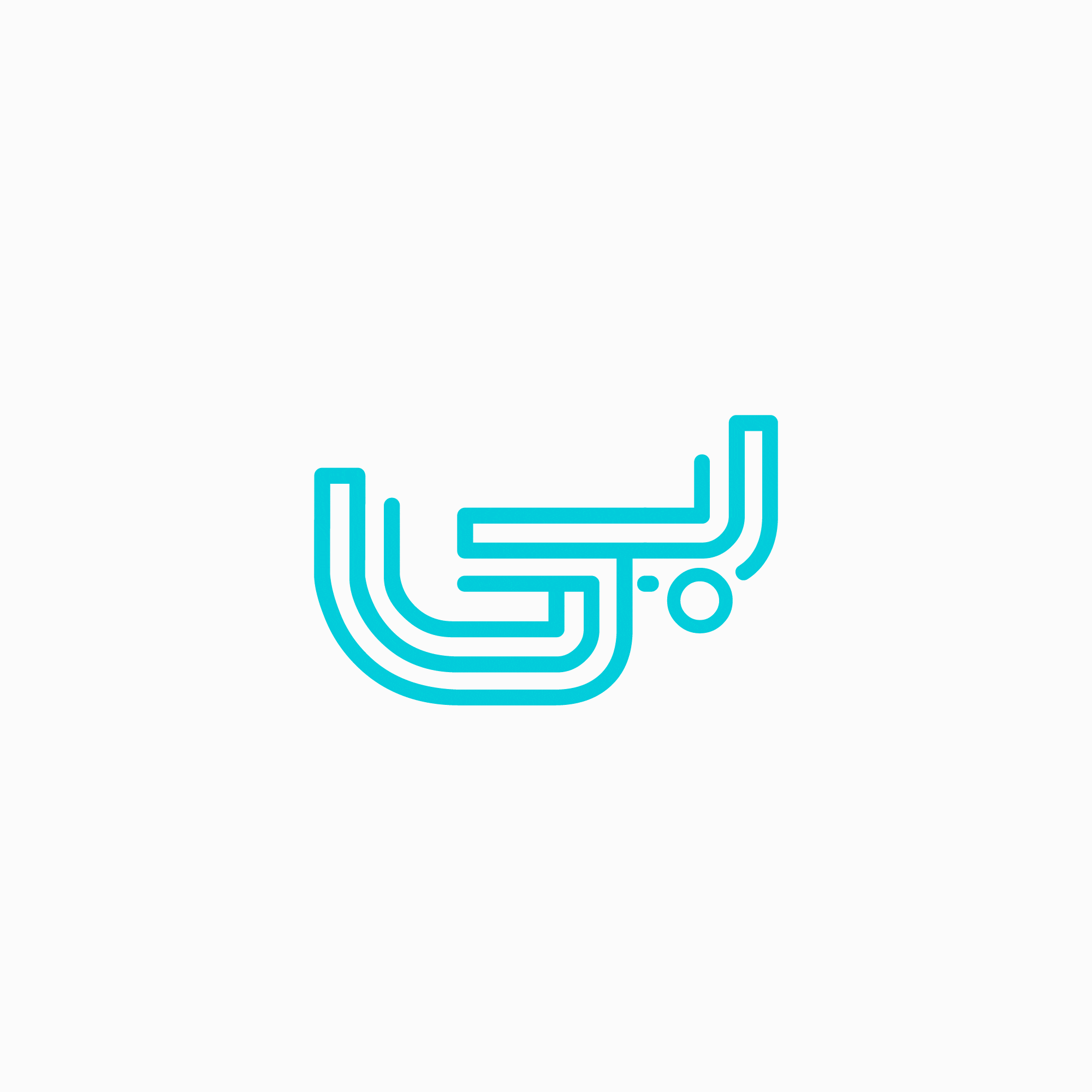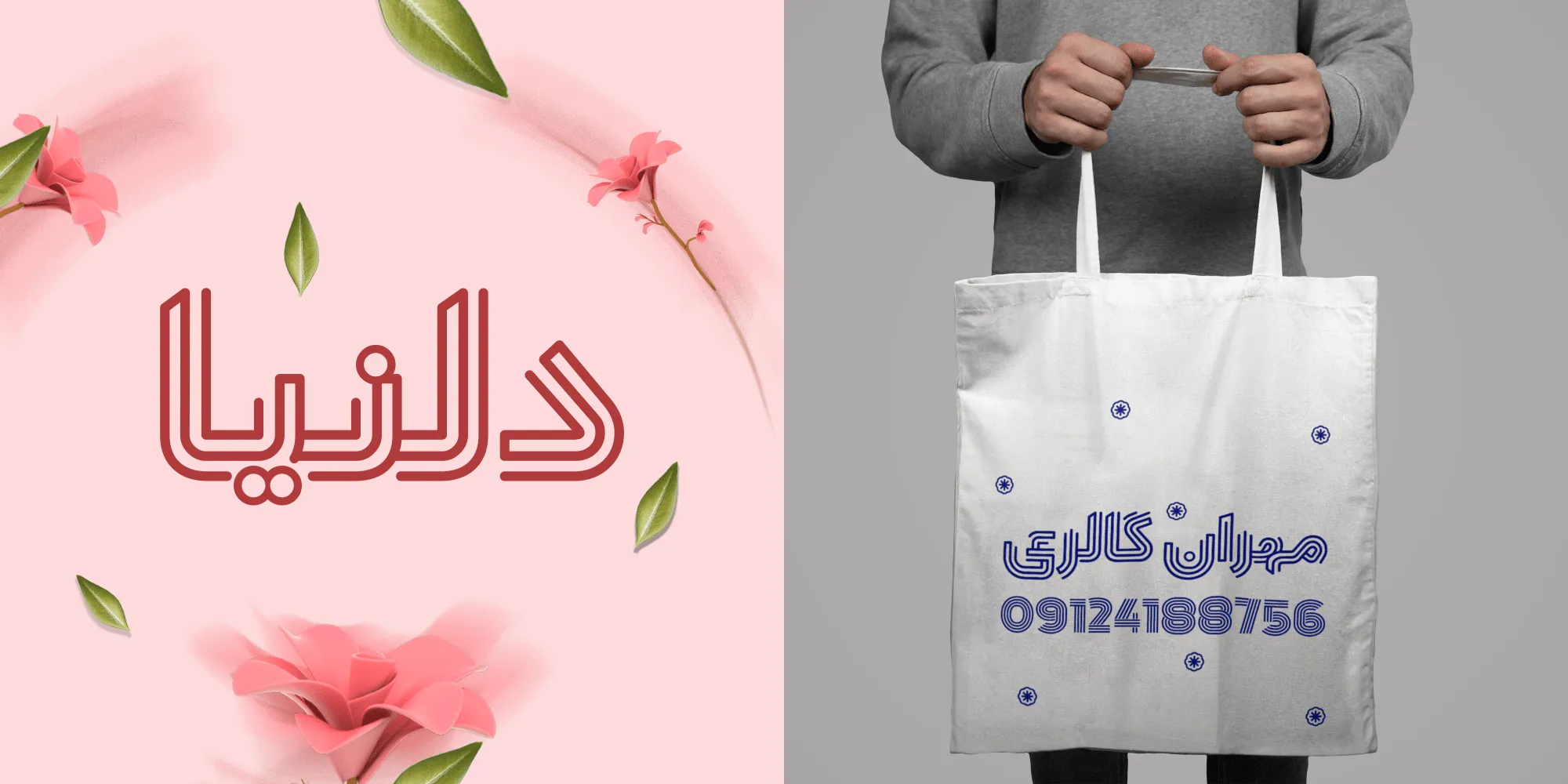
فونت دلنیا (Delnia)
فونت دلنیا (به انگلیسی: Delnia) یکی دیگر از فونتهای جدید فانتزی فارسی است که با سبک مونولاین طراحی شده است که از این قلم میتوانید در کارهای گرافیکی که جنبه تزئینی و نمایشی دارند استفاده کنید. این فونت بر اساس سبک هندسی طراحی شده است. فونت دلنیا رایگان نیست و با توجه به اینکه در یک وزن با قابلیت استفاده از حروف جایگزین، ارائه شده میتوانید آن را در قالب یک بسته نرمافزاری خریداری کنید.
فونت دلنیا توسط مزدک کیانی، طراح تایپفیس و لوگوتایپ طراحی شده است که دارای یک وزن ضخیم Black میباشد که در طراحی تمامی حروف فارسی و غیرفارسی از سبک مونولاین بهره میبرد. توسعه نرمافزاری این قلم نیز توسط امین عابدی که از طراحان و توسعهدهندگان پرکار فونت فارسی است صورت گرفته است.
در ادامه این نوشته از سایت فونتچی به نقد و بررسی کامل فونت دلنیا خواهیم پرداخت؛ قلمی که با توجه به سبک اینلاین میتوانید از آن در انواع کارهای گرافیکی تبلیغاتی که جنبه نمایشی و استفاده برای عناوین دارد بهره ببرید.
فونت Delnia قلمی با ساختار مونولاین است. یعنی با ترکیبی از چند خطوط که به موازات هم قرار گرفته و ظاهری تو خالی از رنگ سفید و مشکی دارند طراحی شده است. این قلم دقیقا ساختاری مشابه فونت ارژن را دارد با این تفاوت که وزن بیشتری را شامل میشود و همچنین خطوط اینلاین، به شکلی درون خطی ادامه دارند.
سبک طراحی و وزن فونت دلنیا
فلسفهای که در پشت فونتهای هندسی، بهویژه آنهایی که با هدف تزئینات و عناوین طراحی شدهاند جلب توجه کاربران است. فونت دلنیا نیز با همین رویکرد با هدف ایجاد مکث و تمرکز خواننده بر محتوا طراحی شده است؛ بهطوری که با صرف زمان بیشتر اطلاعات در ذهن مخاطبان ماندگار شود.
از همینرو با توجه به فضاهای مثبت و منفی در کنار گردش حروف فارسی تصمیم بر آن شد که خطوط بر محیط فرم و گاها در داخل فرم هر نویسه گردش کرده و با ایجاد برشهایی منطقی در فرم نویسهها، این فرصت در اختیار مخاطب قرار داده شود که ذهن او فرم حروف را تکمیل نماید. این امر منجر به افزایش زمان، جهت مطالعهی محتوای مورد نظر را در پی دارد و در نتیجه محتوا نیز در ذهن او ماندگارتر میشود.
پشتیبانی از زبانهای فارسی و لاتین
فونت فارسی جدید دلنیا محدود به این زبان نیست. به لطف اینکه رسمخط فارسی در سایر زبانهای عربی، اردو، کوردی و… که عمدتا شامل زبانهای خاورمیانهای هستند مورد استفاده قرار گرفته است، از این فونت میتوانید برای این زبانها استفاده کنید.
در این قلم نیز مانند سایر فونتهای فارسی طراحی استاندارد تمامی حروف پیادهسازی شده است و اگر مثلا در زبان عربی برای حروف «ک، ی، ه، ؤ، ئ» شاهد نسخهای متفاوت با کاراکترهای فارسی هستیم رعایت شده است تا بر اساس استاندارد بینالمللی گلیفها برای هر زبان طراحی شده باشند.
اعراب در این فونت نیز بهدرستی پیادهسازی شدهاند. بهطوریکه با قرارگیری کاراکترهای «سکون، تشدید و همزه» در کنار سایر اعراب اصلی موجب بههمریختگی کرکینگ کلمات یا حروف نخواهد شد. اعراب با فاصله مناسبی از حر کاراکتر قبلی و بعدی خود قرار میگیرند تا ظاهر کلمات حفظ شود.
این قلم جدای از زبان عربی و فارسی، از سایر زبانهای خاورمیانه ای کردی و اردو نیز پشتیبانی میکند. بهطوری که حروف اردو نظیر «ﮧ، ﮩ، ے» که ظاهری متفاوت از فارسی دارند در آن پیادهسازی شده است.
دیگر زبان پشتیبانی شده در این قلم، لاتین است. فونت Delnia انگلیسی حروف استاندارد این زبان را در خود دارد و میتوانید از آن برای زبانهای لاتین امریکا، انگلیس و… استفاده کنید. بر خلاف اینکه برخی فونتها در بخش لاتین جامعتر طراحی شدهاند تا زبانهایی همچون ترکی استانبولی، فرانسه و ایتالیایی را پشتیبانی کنند، در این قلم شاهد گلیف این زبانها نیستیم.
دارای اعداد کاملا فارسی
دیگر ویژگی فونت دلنیا پشتیبانی از اعداد فارسی، عربی و لاتین است. این فونت هم مانند دیگر فونتهای استاندارد فارسی ضمن اینکه تمامی اعداد این زبانها را در خود دارد، امکان تایپ هرکدام را بر اساس زبان انتخابی در اختیارتان قرار خواهد داد.
در بخش اعداد هم شاهد استفاده از همان سبک مونولاین هستیم که بهصورت خطی اعداد طراحی شدهاند. برای اعداد عربی «۴۵۶» که ظاهری متفاوت نسبت به اعداد فارسی «۴۵۶» دارند گلیف اختصاصی نیز در نظر گرفته شده است.
دارای حروف و ترکیبات جایگزین متنوع
یکی از ویژگیها مهم در فونتهای تزئینی و نمایشی، امکان استفاده از گلیفهای جایگزین است تا بتوان کلمات را در چند حالت ممکن تایپ کرد. این نوع ساختار کمک میکند تا ظاهر کلمات را بتوان در چند حالت ممکن تایپ کرد که به نمایشیتر کردن فونت کمک میکند.
همانطور که در تصویر بالا مشاهده میکنید در این قلم میتوانید حروف و ترکیبات را در چندین حالت مختلف تایپ کنید. از آنجاییکه این فونت با هدف دزدیدن یکباره نگاه کاربر بهصورت اینلاین طراحی شده، پیادهسازی این ترکیبات جایگزین نیز با همین هدف در آن اعمال شده تا ظاهری نمایشیتر بهخود بگیرد.
این حالت جایگزین کمک میکند که در طراحی پوسترهایی که جنبه تبلیغاتی یا استفاده بر روی بستهبندی محصولات، جلد کتب و مجلات یا دیگر کاربردها را دارند، بدون نیاز به انجام کارهای زمانبر گرافیکی ظاهر کلمات را در چند حالت مختلف تایپ کنید تا نمایشیتر شوند.